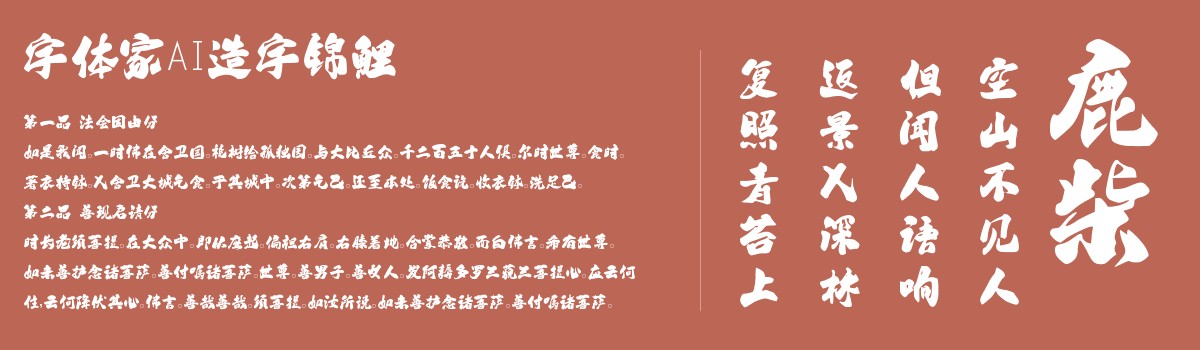
字体家AI造字锦鲤
字体家AI造字锦鲤是一款由字体家AI神笔造字生成的艺术字体,这款字体带着毛笔书写的温润质感,笔画有自然的提按变化:起笔处略顿显沉稳,行笔间渐细见灵动,收笔时或轻挑出锋或圆润收尾,如墨在纸上自然晕染。结构端庄却不死板,横画平稳如担,竖画挺直似柱,撇捺舒展如羽翼轻展,转折处圆融无棱,像指尖轻转毛笔的柔和过渡。整体透着传统书法的典雅气韵,又有手写的鲜活生气,墨色浓淡间藏着呼吸感,像能触摸到毛笔在纸上游走的轨迹,稳重中带着飘逸,沉静里含着灵动。适合用于一些广告标题、平面文案、海报标题、网页广告用字的编辑。